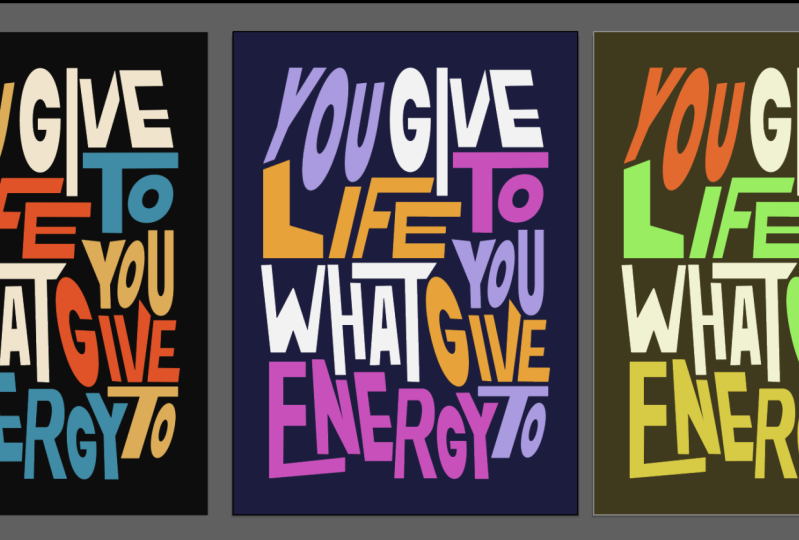
Design de cartaz de tipografia
Introdução ao curso - inspiração e referência
Lição 01 : Como desenhar o primeiro cartaz - distorção tipográfica básica e composição de grade
Lição 02 : Tipografia levou composição - distorção tipográfica individual
Lição 03 : Composição dinâmica de cartaz - distorção de forma e composição
Lição 04 : Elementos finais e pós-produção no Adobe Photoshop
Olá a todos e bem-vindo ao meu curso Skillshare!
Hoje vamos projetar estes 3 diferentes cartazes de tipografia contemporâneo,
A maioria do design será feita no Illustrator usando 3 técnicas e abordagens diferentes para o design e alguns toques finais e desenham alguns detalhes no photoshop
Tenho certeza de que você vai se divertir com este tutorial e você vai ter algumas novas técnicas em sua manga
1. Trailer do curso: Olá a todos. Meu nome é Marcus, animador de designer de animais. Hoje vamos projetar esses três diferentes cartazes de tipografia contemporânea. A maior parte do design será feita no Illustrator usando três técnicas diferentes e três abordagens diferentes para o projeto. E então faremos alguns toques finais e funil. Estes são detalhes no Photoshop. Tenho certeza que você vai se divertir muito fazendo este tutorial. E eu tenho certeza que você vai ter algumas novas técnicas para colocar em sua manga. Então não se esqueça de se inscrever e se juntar a mim na aula. 2. Introdução do curso - Inspiração e referência: Olá a todos e bem-vindos à primeira lição. Primeiro, eu só queria compartilhar com você de onde eu tirei essa inspiração. Estes são, na verdade, estes cartazes. Eu cuido disso. Vi-os no Pinterest e depois fui procurar. Quem foi o designer que começou este tipo de estilo. E porque eu estava pensando que era muito legal e eu realmente queria experimentar com este título também. Então eu gostei de alguns cartazes enchendo isso, fazendo este estilo. E eu só queria compartilhar com vocês o portfólio de designers. Então seu nome é Chris Andrew Small e ele é nosso designer australiano. E assim que vi o trabalho dele, fiquei fascinado pelo uso da tipografia. Eu tenho sido antipática para o último, eu acho, para o último ano ou assim. Tenho andado obcecado com o trabalho de tipografia. Eu tenho visto tanto conteúdo no Instagram sobre como topografia cinética, bem como mover topografia e novos tipos de ondas para usar tipografia normalmente como eu fiz a classe antes, como tipografia, eu senti um ligeiras elifs como no mundo do design vive em um muito, em um tipo muito rigoroso em direção a um mundo sério. E quando vejo alguém fazendo, estou me divertindo tanto com a tipografia e fazendo desenhos tão bonitos e quebrando todas as regras de sempre. Tipo, apenas como obter um tipo e apenas distorcido assim. E experimente cores e contrastes entre as formas. E então apenas criando isso como composições interessantes com ele. Eu estava fascinado com o seu trabalho e eu só decidi explorar um pouco para mim mesmo, algumas pausas caindo neste estilo talvez tentou obter algum conhecimento são liberados também porque o Ártico é como, não é como ele tudo bem para se inspirar e às vezes até copiar outros. Pessoas, designers trabalham porque você parece que tentou recriar algo. Você realmente tentou entrar na mente daquela pessoa e tentar ver o que ela vê. E nunca mais será o mesmo porque você sempre terá sua própria opinião sobre ele. Não é como se eu estivesse apenas criando o Saclay, este aqui. Agora, você só vai usar o mesmo tipo de estilo, mas isso nunca vai ser a mesma voz porque isso é exclusivo para você, como se sua abordagem fosse diferente. Por isso, está tudo bem se você apenas inspirar-se onde outras pessoas, Tenho certeza Chris, Andrew Coats inspirado por alguns em algum lugar também. Assim como uma mistura de respirações e realmente só queria compartilhar com vocês este é o portfólio primeiro porque eu acho que é realmente, eu não acho que você deve verificar. E eu acho que é incrível. 3. Aula 01: como criar o primeiro pôster — distorção de tipografia e composição de grade: Então eu vou mostrar primeiro que repórteres vamos projetar. Então o projeto final será feito para uma loja. Na verdade, isso é exatamente como as formas vetoriais. E o primeiro que vamos começar é este. Outra coisa que eu queria compartilhar com vocês é que eu criei uma biblioteca para este curso, que vai estar em seus arquivos Skillshare. Certifique-se de baixar a biblioteca. Você terá as cores e a arte real. E para isso, basta ir às bibliotecas aqui. Se você não tem a guia da biblioteca aqui, você pode simplesmente ir para Janela e tentar encontrar suas bibliotecas aqui. E depois vamos para a biblioteca Importar. Selecione o destino da biblioteca. Eu já salvei o meu aqui. Então você vai ter este arquivo na pasta. E assim que importamos, basta clicar em abrir e importar. E você vai ter todas as cores que eu uso nesses cartazes. E os cartazes reais e reais no caso de você querer abri-los e dar uma olhada. Se você apenas clicar e arrastar e soltar assim, você vai simplesmente soltá-lo. Se você quiser ir para dentro do vetor, você pode simplesmente selecionar Embed (Incorporar). E então nós vamos apenas incorporar a arte aqui e você pode apenas desagrupar e , em seguida, liberar a máscara de recorte. E tudo o que você tem agora é um arquivo vetorial. E você só precisa liberar máscaras de recorte até que você realmente tenha toda a capacidade do arquivo. Bem, vamos começar o nosso primeiro cartaz para que as escolas de direito se tornem novas. Vamos mostrar-lhe esta resolução realmente vai torná-la vertical 358 por 4961. Isto é mais ou menos como um cartaz A3. Então vamos dar um nome a este cartaz do Skillshare. Um. E vamos pressionar Ok. Desculpe se estou falando rápido demais. Tento não fazer essa aula esperar muito tempo. Eu não sei. Eu sinto que às vezes eu gosto de ser como sótão é mais dinâmico se ainda ensino é digitado até a velocidade e não leva muito para aqueles funcionários ou explicando ou muito lento. Eu gosto de mantê-lo, mantém-me incrível envolvido na classe. Então, para essas classes, eu realmente uso algumas citações inspiradoras de um Oriente Médio na verdade, e eu tenho que compartilhar isso em arquivos também. E DC era como alguns pedidos de inspiração como da frente, mesmo de Provérbios Chineses, dois filósofos para músicos, até intrapreneurs atuais. E é como eu faço, eu faço lei, eu acho que é como se houvesse muito poder nesses códigos. E às vezes eu os leio e eles fazem é como Orozco para mim. Às vezes eu os leio e eles me inspiram ou fazem sentido para mim naquele momento. Então eu gosto de ler um pelo menos por dia e eu gosto de usá-los tanto quanto eu posso para o meu trabalho pessoal, que foi o que eu fiz naqueles cartazes. Então o primeiro que você vai usar é de uma abundância de Napoleon Hill. E um objetivo é um sonho com um prazo porque você não quer esse arquivo. Ele estará na pasta Skillshare. Selecione qualquer um desses códigos como quiser. É que eu tentei não usar muito longos porque ele vai te dar mais. Você pode selecionar o tempo que quiser. Mas quanto mais palavras você tiver, mais tempo você vai precisar para colocar cada palavra, que pode ser mobília como você tem mais para experimentar por todos, apenas tente usar como uma muito curta por enquanto. E talvez depois de fazer este curso, mesmo se você fizer este tipo de estilo novamente, você deve explorar como esperar mais com certeza. Então eu vou usar este aqui. Vou copiar e colar isto. E eu vou usar a ferramenta de texto no Illustrator para apenas colar a escala de canto. Um sonho é um objetivo. Um objetivo é um sonho com um prazo. Bela turnê. Eu realmente gostaria de usar realmente um muito bom, como um VLC cubículos de ética é uma fonte que funciona como você faria qualquer coisa. E quando eu não tenho certeza que tipo de fonte eu vou usar para qualquer projeto. E se e se ele for como um projeto cliente, 90% das vezes eles já terão uma fonte. Mas se eles não têm, eu vou para o cuidado veterinário ou algodão ou para turnê. E eu só vou para o personagem aqui. E eu vou fazer tudo isso. Então vamos apenas, a primeira coisa que realmente você precisa fazer é expandir seus testes, seu texto. Certifique-se de que está satisfeito com o código. Porque assim que expandirmos isso, não seremos mais capazes de editar o texto. Se você quiser pode apenas fazer uma cópia disso, talvez ir para editar. Copiar, Editar, Colar. Deixe aqui apenas por segurança, caso queira alterar isso por algum motivo ou alterar a fonte. Então vamos começar. Vamos para Object e ir para Expandir. Imprensa. Está bem, Perfeito. Então a coisa sobre o estilo que eu mais gosto é de laticínios, sem regras sobre como você trata a fonte dele. Você pode esticá-lo para cima ou para baixo. Você não precisa realmente gostar, você sabe, quando você está projetando, você precisa realmente estar procurando o kerning e tentar entender distância e enquanto as proporções e como, é tão, é tão chato às vezes . E o estilo é tudo, mas não erro chato. Então, a maneira que eu gosto de fazer isso é apenas, vamos começar separando as palavras. Um objetivo é um sonho. Prazo. Ótima. Então você pode realmente, se quiser, você pode começar a criar algumas formas primeiro. E como vamos usar a ferramenta Retângulo, por exemplo. E apenas tentando criar algumas como começamos, formas aleatórias. Você não precisa seguir nenhuma nota. Podíamos fazer uma grelha e seguir a grelha, mas isto é para ser tão livre quanto nós, quanto pudermos. Acho que se todos puderem lê-lo como designer, já temos regras demais. Então vamos saber se temos regras aqui e não há grades em tudo. Então, vamos apenas para aqui. Você pode ir para a luz que você elaborou, manter apenas importante e usar minhas cores, se você quiser. Caso contrário, você pode simplesmente ir para as amostras de cores aqui. Encontre uma amostra realmente agradável para o seu cartaz. Adoro o Papa devastado pela guerra. E você pode simplesmente explorar todas as cores incríveis que já estão nas bibliotecas do Illustrator. Ou você pode simplesmente ir para equipes de cores e tentar encontrar uma cor realmente agradável para ele e apenas usado para ele. Não se sinta forçado a usar minhas cores. Por favor, tenha certeza que está. Você realmente explorar mais cores e eu vou tentar não gastar muito tempo em cores nesta classe porque eu queria fazer uma carga. E, mas eu tenho certeza que você pode apenas usar este Explorer na cor, Adobe Color Themes será, você está pronto para ir. É uma seleção incrível aqui. Só vou fechar isto por enquanto. Então vamos começar. Então você pode começar como eu disse, como apenas bloquear algumas formas ao redor e então usar seus textos. Eles estão tipo, eu estou pensando em talvez como esta forma preta aqui. Vou ao Comando C, comando F para colar no lugar. Vou fazê-lo usar esta cor rosa aqui. E agora vou me fazer perder minha primeira palavra. Vou fazer isto largo. Vamos apenas selecionar este sólido preto porque ele está na frente de uma carta e eu vou arrumar e vendê-lo para trás. E eles vão usar esta ferramenta de distorção aqui, a ferramenta de transformação livre. Se você clicar em E, apenas vai empurrá-lo para cima. Aqui. Isto é, é bom fazer isto. Por alguma razão. Se meus diretores de arte, alguns fazendo isso com o nosso, no nosso trabalho, ela só vai mostrar, apenas me matar. Não posso fazer isso com fontes. Mas a coisa é como, eu acho que nós, nós devemos ter tempo para jogar. Eu acho que é quando você parar de jogar e se divertir com o design é quando você começa, quando você apenas diz quando ele começa a ser apenas um trabalho e não como um hobby ou como realmente algo que você gosta de fazer? Eu acho que para eu não jogar por anos. Como designer, eu só tinha trabalho de cliente e eu apenas fiz isso, eu não sei, por um longo tempo sem fazer nenhum experimento pessoal ou projeto pessoal. E eu podia sentir como se eu não fosse Thai Wah começar a odiar. Mas eu estava começando a não gostar como eu costumava desfrutar do meu profissional como quando eu comecei. Então este é um, eu vou apenas arrastar o objetivo agora, clique com o botão direito do mouse. Traga-o para a frente. - Sim. Então eu acho que é importante também para você, assim como, você sabe, é importante para você ir lá fora e dar um passeio na natureza. Eu acho que é importante também, ir lá fora no Illustrator e apenas ter um, ter um ir. Apenas se divirta, sabe? Não, apenas criando algo. Ou mesmo assim como eu fiz, apenas ir como no Pinterest, encontrar algo realmente legal e tentar recriá-lo de alguma forma e tentar torná-lo o seu site, para torná-lo o seu estilo. Então agora, como se eu estivesse distorcido é um pouco, mas em um objetivo, eu realmente quero começar a distorcer o isqueiro como igual. Eu quero fazer alguns deles mais. Talvez como eu faça as distorções individuais. Em vez de ser um grupo mais velho. Como este. Talvez a fazer algo assim. É só que talvez você vá levantar essa perna. São todos distorcidos ainda mais do que um, algo como. Então, o primeiro pôster, eu só quero pedir para explorar como apenas distorções de escala, não como tantas rotações. E é como um aquecimento para o que vem a seguir. Então o objetivo é que eu vou, eu realmente não posso fazer o simples, desculpe eu fiz antes. Isso. Como exemplo, eu te mostrei aqui. Porque é como, ele, realmente depende do momento em que você está fazendo isso. É como se toda vez que você vai fazer este processador, ele vai recriar. Ele terá um olhar diferente projetado para que a técnica será definitivamente a mesma. Assim como explorar formas e formas. Um gol. Talvez você possa escalar esses dias para jogar com contraste líquido e posição também. Você sabe, como um gol, você não precisa. Mais uma vez, temos esta caixa aqui para, para referência. Embora possamos, podemos brincar com a caixa o quanto quisermos também. Você não precisa ser muito precioso sobre, sobre a caixa. Como, novamente, nós não queremos grades é como diretrizes que não podemos seguir era. Então um objetivo é, vamos apenas agora fazer é um objetivo é meio como este, mas são realmente precisa fazer é criar alguma separação entre as letras. Caso contrário, parece que ele é a mesma palavra como goleiros, em vez de dois momentos diferentes do vocabulário. Isso faz sentido. Oh desculpe, eu só uso um atalho, mas você pode apenas selecionar a forma aqui e organizar e enviar para, você tem o atalho aqui. Vou mandar para trás e providenciar. Enviar para Voltar. O objetivo é apenas talvez escolher, talvez mudanças muito largas. Talvez voltes a brincar com a esfera de distorção. Por favor, certifique-se de encontrar como obter como um código realmente agradável a partir dessa lista e, e jogar ao redor. A realmente quero ver como porque eu tenho certeza que algumas pessoas vão escolher os mesmos códigos para. Você pode até adicionar como eu fiz agora. Você pode simplesmente adicionar novos elementos à sua fonte. Não há nenhuma promessa. Erro. Ir embora estava dizendo que é exatamente como eu tenho certeza que algumas pessoas vão escolher o mesmo, o mesmo frio, a ferramenta Simcoe falar com pessoas diferentes. E eu realmente quero ver como, como, como você é isso, como você desenha, como será diferente ou você sabe, como algo como duas pessoas podem ter o mesmo código e devido a dois diferentes projeta cuidadosamente. E até mesmo a faculdade, eu acho que as cores nesses exercícios são tão essenciais porque é como se você estivesse brincando com contraste e formas e você está definitivamente confuso com todas as regras da tipografia. Mas a cor também ajuda, como ajuda muito a mensagem aqui. Vamos continuar mudando isso até que pareça certo. A coisa se um telefone às vezes projetar é um pouco como É um pouco de um sentimento. Às vezes é como você, você sente que não está lá ainda, mesmo quando parece bom. Vamos continuar empurrando. E então é, então você prazo para o que é leste o fio é projetado e o que é arte torna-se realmente difícil de definir para mim, pelo menos. Por isso, às vezes penso que o design é uma conjunção de função e arte. E não sei se isso é uma corrente. Onde é que é isso? A Nike também é branca. Talvez eu distorça este slide. E novamente, você, isso, isso é sobre apenas experimentar e descarregar tudo. Isso é sobre como se você é um diretor, diz que isso é sobre fazer, estão realmente com fome ou Ei, eu estou realmente com raiva. Como o quê? O que você está fazendo é descarregar o objetivo está bem, legal. Apenas empurre isso. Talvez, na verdade, nós vamos então nós vamos fazer isso um objetivo é. E então talvez você possa apenas continuar experimentando até que você sinta que está certo e você pode sempre voltar aqui. E a justiça. Agora vamos usar escala aqui. Então esta é a escala de uso. Sim, Então, para vir enchendo mais melhor , este aqui, às vezes, é complicado jogar com o contraste das formas também. Sim, acho que acha que estou feliz com isso. E agora vamos sonhar. Então, até você usar o mesmo estilo que eu uso em um primeiro pôster, que eu uso o A para preencher todo este espaço. Cria uma forma muito agradável. E como esse tipo de efeito de flecha, que é muito legal. Então eu vou apenas fazer uma nova caixa aqui usando a ferramenta de retângulo aqui. E eu vou encontrar uma cor para isso. Talvez possa ser azul. Rosa agora, filtro azul, certo? Por que eles estão realmente bonitos? Então, quando terminarmos todos os cartazes, vamos levá-los ao Photoshop. E lá vamos fazer, adicionar um pouco mais de detalhes, como alguns rabiscos sobre ele então. Mais como mais detalhes de ruído e tornando isso um pouco mais interessante. Então, tudo bem se você sair como um espaço vazio como este. Porque então podemos, podemos ter mais, alguns detalhes sobre para um SharePoint que, como você vai ver em breve. Um objetivo é um sonho. O sonho é um sonho. Então palavras realmente bonitas que chamam de um sonho, mas eu vou apenas distorcido como este chamado os olhos Filson. E mesmo como, sabe, quando você faz isso, você sente como se estivesse destruindo. Mas é apenas tornando a deformação mais, mais interessante é como apenas tornar isso mais útil para o, para os olhos. Sabe, é mais interessante porque se você colocar isso na moldura branca deles usando o lago, está tudo bem, você recebe a mensagem e é importante, mas quando você faz assim, Você recebe a mensagem e recebe outra coisa. Há algo diferente. Você tem uma sensação de letra diferente. Você vai ler. E você também experimenta uma sensação ou social o suficiente como talvez você não goste, mas ainda assim uma sensação, parece que um sentimento está lendo e algo diferente não é apenas ler está experimentando uma mensagem. Acho que no Dream é uma árvore. Eu vou apenas fazer isso. E talvez moeda para. Só tenha certeza de que não distorce muito. Então você vai realmente perder a forma da letra. Você ainda precisa entender que dizer que eu sou um a e um são de outra forma, então você a mensagem será, não será tão clara quanto precisa ser, para ser capaz de lê-lo não rapidamente, mas para lê-lo. Como se você não quisesse ser como algo irracional no único A-frame. Caso contrário, você pode apenas obter os interesses para o visual, mas então você pode perder o interesse pela informação. E a informação também é, é. Também é importante como, tão importante quanto um visual. Só vou selecionar isso. Um objetivo é um sonho com um prazo. vez, temos uma letra um, que é como realizado, citado porque eu gosto do porque alguns seta Osaka o tempo todo. Só resolvemos uma fonte Attica. E eu gosto desse sentimento de como apontar para algum lugar. E a dinâmica de um tipo de esconderijo mostra que eu realmente, bem. Só vou usar preto. Perfeito. É um sonho com um prazo. Não sei se vou tentar isto. Talvez ele crie como um pouco de boca, mais dificuldade para entender o que está escrito aqui. Usando um teste como este. Mas acho que cria um visual agradável e agradável também. Eu acho que ele cria como um bom nome dinâmico e matriz porque você tem um objetivo é um sonho. E depois vamos para baixo com esse prazo. Nós bactérias vamos sair assim, apenas certifique-se de criar um fundo sólido. Faça-o branco. Empurre para trás. O objetivo é um sonho com um prazo. Talvez possamos tocar um pouco para a composição aqui. A estrela para também ter certeza de, como distorções personalizadas para cada letra é que ele cria como uma outra camada de interesses de interpretação assunto sobre ele. Como traços indo para, talvez você está indo para empurrar o a e fazer o n. Então eles não têm como o, porque quando você interrompe-los completamente, ele ainda sente que eles são dados como esse. É que esse é o estilo deles. E quando você faz distorções diferentes para cada um deles? Você pode sentir que, oh, este é realmente um novo dia diferente. Isso é, na verdade, talvez um por um. Só vou adiar o prazo. É só ver se funciona. Agora, como você pode ver, às vezes funciona muito bem horizontalmente. Ele realmente precisa funcionar bem na vertical. Então eu só vou, talvez eu apenas empurre isso assim. Então não faço outra maneira. Sim. Então este é o primeiro. E depois de desenhar o cartaz seguindo esse tipo de solução, eu meio que gosto de relaxar no pulsar de alcatrão e então eu vou agrupá-lo. E agora L, quando você se move, você apenas selecioná-lo e você se move. Tão completamente. A próxima coisa que vamos ser percebidos a fazer é, na verdade, reduzi-lo um pouco para baixo. Vamos matá-lo como 90 por cento. Algo como isto. Eu faço isso porque eu realmente gosto de assinar esses cartazes. Como se esse código fosse. Vamos colocar como frio pelo tamanho é chamado Napoleon Hill. Então precisamos dar algum crédito para o, para o código mais quente. Citação de Napoleon Hill. E habilidade este pouco para baixo. Talvez 35. 35 aqui. Vamos fazer um desenho de Marcos. E faça o mesmo. Certifique-se de dar crédito ao, para o criador do código. E, novamente, também dê crédito para o design do portfólio. E não se esqueça de, se você, se você tem Instagram ou alguns alguma rede social, se você postar o eficiente é, por favor, certifique-se de me marcar. Eu adoraria ver e compartilhar seu trabalho também. Meus, meus, meus seguidores. E eu realmente gosto de permitir realmente como quando, quando realmente ver como o que vocês fazem quando vocês postam projetos na seção de projetos da classe? Diz que toda vez que temos uma notificação e eu vejo, é tão bom para mim porque é como, oh, alguém, eles são, alguém realmente teve tempo para fazer essa aula. E eu espero que eles gostem de cada um de mim também vendo o trabalho de finalistas, você sabe, porque é como se isso tornasse minha classe mais real para mim de alguma forma. Então vamos fazer um aqui. Vamos apenas alinhar isto. Certifique-se de que não precisa. Bem, por que não? Só fazer uma parada completa por aí? Sim. Então, sim, este é o nosso primeiro pôster feito. Teremos este pulsar no Photoshop mais tarde, quando tivermos todos os pulsares de árvore. E então vamos fazer alguma pós-produção em todos eles de uma só vez. Então, não precisamos pular do Photoshop e voltar para o Illustrator. Vamos fazer nosso próprio trabalho no Illustrator agora. E depois saltamos para o Photoshop. 4. Aula 02: tipografia em composição — distorção de tipografia tipográfica individual: Olá e bem-vindos ao segundo cartaz. Então vamos usar a mesma resolução de antes, 3008 por 4961 orientação vertical. E isso é ótimo. Assim, o primeiro redesenho do cartaz, este aqui, usamos formas para nos ajudar a, para a composição dos textos dentro dessas formas. Então este é um bom exercício para começar, como porque é, é mais fácil encontrar o equilíbrio certo. Nós moldamos primeiro e depois exploramos os textos dentro dessas formas na literatura do segundo cartaz. Então abertamente exemplo aqui, nós realmente queremos usar os textos como, como o centro principal da composição. Como não temos nenhuma forma aqui, vamos brincar mais com o peso do texto. Então nós apertamos, nós íamos distorcer um pouco de textos, um pouco mais. Vamos girá-lo. E toda a compensação será liderada pelo texto e pela topografia. Então vamos pular. Então adotivo dois são usados. Outro casaco e novamente está nas listas. Eu só compartilho com você, desculpe, e palpites. Meu cérebro começa a ficar congelado porque eu gravo essas aulas na noite em que minha namorada está assistindo TV e eu terminei meu trabalho. E eu digo: “Sabes que mais, vou fazer uma aula de Skillshare”. E, às vezes, sou um pouco cansativo e o meu cérebro pára, tipo, o que mais dizer a seguir? Tentei fazer roteiros para essas aulas, mas piorou as coisas. Então eu não sou agora eu sei o que eu vou fazer. Faço a aula primeiro comigo mesmo e depois tentei recriar o exercício. E a ação se sente melhor porque se sente evento mais natural para mim. Tão arrependido. Depois disso separados. A cota que você vai usar é um investimento em conhecimento, paga o melhor interesse de Benjamin Franklin. Na verdade, Benjamin Franklin, nota lateral, é um ser humano muito interessante. Tenho aprendido sobre coisas de saúde como dormir melhor e jejum. E Benjamin Franklin, ele apenas, ele era apenas um incrível como a maneira como cuidar de seu cérebro e corpo era algo insano. E é realmente um cara muito inteligente, com certeza. Portanto, um investimento em conhecimento paga os melhores interesses. Bem, Skillshare está aqui para provar isso. Vamos fazer essa aula. Desculpe, vou parar de falar sobre funcionários que não são relacionados à aula. Então vamos copiar e colar novamente aqui. Um investimento em conhecimento com as notas de melhor interesse. Sei que, na verdade, tenho feito design há menos de 10 anos. E as melhores coisas que obtenho da minha carreira é como o Times realmente aprendeu com outras pessoas e com os cursos que fiz quando fui, na verdade, começaram a minha carreira. Skillshare não era uma coisa ainda. E eu costumava comprar DVDs online e o era tão caro e nos escapa como nós, eu e meus amigos da universidade vamos ficar juntos. E eu acho que como se fosse uma série que custaria como algo como 200 Euros de GetNumWords, escola de efeitos visuais e para After Effects. E nós só nos juntamos e compramos juntos e depois compartilhamos os DVDs um com o outro? Bem como diferentes épocas e 200 anos, 10 anos atrás era muito dinheiro para nós. Ainda muito dinheiro, mas foi divertido e eu realmente ensino no Skillshare porque é tão acessível para todos. E, você sabe, é como se pudesse ser algo realmente profundo sobre alguma técnica, ou poderia ser apenas algo que fica muito divertido de fazer. E podemos fazer isso juntos. E eu nunca tive como este tipo de e mesmo como os tutoriais sobre Skillshare são mais experimentais e 1980, é algo realmente interessante para mim porque como você não segue passo a passo e você todos nós temos o mesmo resultado. No final, você sabe, antes que eu pense que os tutoriais são usados para adivinhar, obter como 10 anos atrás, os rendimentos seguem passo a passo. Você vai gostar de um livro de receitas. E no final, você será r teria o mesmo reforço ou o mesmo design. Exatamente o mesmo. E os cursos que eu tenho feito, feito no Skillshare principalmente é tão criativo, é mais criativo orientado com preto. Você pode aprender uma técnica e desfrutar de explorar. E eu nunca vi duas pessoas terem sido vários resultados. Então vamos começar com isso. Sinto muito pelo meu murmúrio agora. Eu só queria compartilhar isso com você. Ok, então qualquer investimento em conhecimento paga os melhores interesses. 70. Mais uma vez, vou financiar obter LV Attica. Outra dica é se você já assistiu o velho documentário da Vertica, veja isso é, É realmente incrível. E vamos ao Object e ao plano X. Ótima. Cmt nos permite selecionar prêmios e desagrupar isso e colocar portas distância uns dos outros. Então, você sabe, eu realmente esqueci de fazer isso tudo em maiúsculas. Eu fiz um monte de comentários. Sr. E todos os bonés. Talvez não. Bolt. Vou criar esboços. Você pode clicar com o botão direito do mouse e criar contornos, ou ele pode ir para Objeto e ir para Expandir. Mesma coisa. E você também pode ver que o atalho é Command Shift O e os contornos que x é a maior coisa que enquanto software há milhões de maneiras de fazer uma coisa. E vamos para um investimento na base de conhecimento. Os melhores interesses. Na verdade, isso já é, pode já ser alguma coisa. Acho que gosto da forma como esta é a dinâmica dos decks acontecendo aqui. Um investimento em conhecimento, talvez o conhecimento deva ser um pouco baixo. É como um passo. Se você gosta top poucos oferecem alguém passos. Está bem, mas não é isso que vamos fazer hoje. Então vamos selecionar n e apenas usando a ferramenta de transformação livre, Vamos começar a distorcer isso é fede primeiro, e vamos apenas empurrar este também. Então, ok, vamos apenas, então agora nós vamos realmente tão doce, não temos formas. Nós vamos realmente usar o tipo para criar algumas composições dinâmicas como esta. Só vai ganhar vai apenas torcer assim e então talvez brincar com o n. Talvez seja apenas empurrar o N um pouco. Como na verdade, vamos, vamos ver, vamos ver o que é o que os textos nos dirão e investimento. Ok, eu posso ver isso acontecendo. Oi, Miguel. empurre o “N Talvezempurre o “N”. Eu só vou fazer isso. Ok, não vamos esquecer de usar as novas cores se você quiser. Se você não quiser, por favor, não se sinta forçado a usá-los. E só tentando distorcer essa coisa. Novamente, apenas tendo o máximo de diversão que puder. Como ninguém está olhando, ninguém está aqui para julgá-lo. Eu acho que não ser louco é a coisa louca é apenas empurrar isso para baixo e tentar inovar. Tente encontrar a perna direita. Composição como técnicos de rádio tentou empurrar, diz, tentou ser negrito que você não precisa gostar, e se não está funcionando no escopo de volta nota inicial. Então, de uma maneira diferente. Talvez seja uma separação melhor entre o tipo e as letras. E eu só vou empurrar isso. Agora você não quer perder um vicioso indo para um investimento e apenas tentando fazer isso. Você também pode selecionar os pontos usando a ferramenta de seleção. Se você clicar em um também, você não pode simplesmente puxar esses pontos e novo, você apenas distorcer a tipografia ainda um pouco mais. E veja o quão longe você pode realmente chegar. Eu tenho outra classe no Skillshare e que é criar um formulário diferente usando fonte antes. É topografia personalizada do experimento, por favor, confira. Sim, tenho certeza que se você tivesse gostado desta aula, você não iria gostar dessa também. Vamos empurrar isso para baixo. Tente jogar com isso como usar um novamente aqui. Talvez só empurrar isso. Há um líder. Como se não estivessem lá. É que às vezes eu não quero lutar com ilustrador sueco e tudo bem. Experiência talvez, na verdade, quando há um aqui, eu vou distorcido t. novamente. Certifique-se de não ter medo de fazer edição porque é, É apenas experimentos que você realmente, quando você joga é quando você realmente aprender mais, é quando você realmente, você pode levar isso no futuro para algo Totalmente diferente. Você sabe, como quando você aprende que, como uma nova técnica que você aprendeu nesta aula, que então você pode usar realmente para o seu trabalho real ou a vida são totalmente diferentes exercícios, mas é quando você explora como aqui. É, você nunca sabe onde, onde isso vai te levar, ou quando você realmente vai usar isso, ou quando você quer realmente ter a chance. Imagine se você tiver a chance de, na verdade, alguém vê seu pôster e diz: “ Oh, eu quero isso. Será porque você o explorou. Não seremos porque está em você, porque é exclusivo para você. E essa é a beleza de não fazer um design tradicional. Pratos de cartaz porque se torna único, é torna-se diferente e Garros mais atenção. Então, quanto mais você jogar, melhor. Vamos continuar empurrando isso. Eu gosto da forma como isto, isto, esta rede que eu gosto de trabalhar em negrito não são realmente, não tenho certeza sobre alguns deles na verdade, talvez o n é parece realmente distorcer este pouco mais. Sinto que estamos perdendo alguma legibilidade e investimento. E mais uma vez, está tudo bem. Você pode apenas, você pode apenas realmente usar também algumas ferramentas para distorção de padrão. Isso é apenas pode selecionar este grupo que. Então ferramenta de distorção novamente. Oh certeza de que você pode apenas brincar com como tentar distorcê-lo usando nossa ferramenta de cisalhamento aqui, ou mesmo como nossa ferramenta de forma. Agora, na verdade, vamos brincar com essas ferramentas de movimentos aqui, a ferramenta de cisalhamento que eu acho é que ele ajuda muito sempre que queremos experimentar com uma perspectiva diferente sobre isso, em um texto. Como se você não se sentisse muito feliz com a posição. Você pode simplesmente brincar com a ferramenta de cisalhamento e ver onde ela o leva. Principalmente. Você vai apenas fazer isso. Então, o “A” realmente se senta lá, algo assim. Só estou tentando jogar assim. Perfeito e investimento em, costurado é uma coisa grande e nós só precisamos fazê-lo. Porque enquanto você lê isso, você vai querer ter certeza de que você mantém o, a seqüência do código indo. Então vamos apenas para n e apenas jogar um pouco também é, mas não muito louco. Por isso, não perdemos o significado deste casaco. Como não significar sua legibilidade deste código. Desculpe, um investimento. Conhecimento. Então o barulho tem um muito grande. Talvez possamos brincar um pouco mais com conhecimento. Só vou empurrar isso para cima. Acabei de começar. Empurre aqui. Chumbo. Eu posso destruição individual como para tornar o texto um pouco mais interessante. Não perder totalmente a forma da letra. Talvez usando um empurrão. Sim, algo assim. Podemos brincar com a posição das letras também. Portanto, não é uma distorção, mas também algumas composições dinâmicas com a posição das letras é um investimento no conhecimento. Veja como, mesmo como agora, parece tão dinâmico e você ainda pode lê-lo. Você provavelmente vai levar um pouco de tempo. Quando você leva mais de dois a cinco segundos para lê-lo, talvez ele deva apenas como eu acho que é como ver o que está impedindo. Não está a ajudar-te. Neste caso. Eu acho que o n, É talvez um pouco de lata e nós realmente perder a capacidade de lê-lo como o fim realmente rápido. E provavelmente vou tentar fazê-la voltar a ser um pouco legível como nós antes. Só vou selecionar assim, talvez usando nossa ferramenta de cisalhamento novamente. Ou talvez apenas na verdade vai apenas apagar este n. Eu vou usar este aqui. E eu vou usar este aqui porque não há problema em fazer isso. Um investimento em conhecimento. Eu acho que conhecimento e experimentação, há um monte de periodontal de conhecimento em experimentação e experimentos, mas foi, não, foi medo de experimentar definitivamente não é. Um investimento em conhecimento, paga o melhor interesse. Novamente, talvez eu esteja indo para jogar com p. E eu vou, usando a ferramenta de seleção aqui, poderia empurrar esses pontos um pouco. Uh, como esta peça clínica, uma carta tão bonita para brincar. Porque é a forma da letra P é algo como Laker é como uma Tammy algum como se isso faz sentido, é como um guarda-chuva, tipo 5. Você vê, você pode colocar algumas letras aqui embaixo e fica muito bom. Novamente, alguma distorção individual como esta. Talvez, talvez por que nossa vontade de realmente ampla pode apenas ok. Dividir. Vamos brincar com a largura assim, como a maneira. Embora eu acho que devemos brincar com alguma parte dessas cartas com certeza. Vamos usar o cisalhamento para tentar não perdê-lo. Basta usar a ferramenta de distorção livre. E tente encontrar uma boa composição para isso. Ok? Paga o melhor. Veja, isso já é uma citação muito longa, que está me dando um pouco mais de trabalho para redefinir tudo. É por isso que eu disse, se você tentar, se é a primeira vez que você está fazendo este exercício, certifique-se de usar como um código mais curto para a primeira experimentação. Então você não passa menos tempo fazendo a composição e mais tempo brincando com ela. Você sabe, porque quantas cartas você tiver, mais difícil será. Portanto, apenas esteja ciente dos dados, na verdade, apenas esteja ciente de que você provavelmente vai se sentir provavelmente apenas fazendo isso pela primeira vez. Esteja ciente também. Para tentar encontrar como um código muito bom, fácil para o, vamos apenas brincar. Veja você pode, você pode até mesmo estender letras para que eles realmente se conectem uns com os outros de uma certa maneira. O conhecimento, base de conhecimento são os melhores interesses? Então as abelhas são realmente interessante letra bem para trabalhar. Então isso é apenas um interesse é uma palavra muito longa, mas vai ser um ritmo certo. A melhor habilidade desta prática, brincar, contrasta. Como você pode ver aqui. Nós apenas torcemos uma matriz muito magricela aqui e muito ousado B e T e este bonito como talvez escala isso. Jogar com, com movimento, bem como uma pequena dinâmica como você pode fazer a sua conclusão, o melhor, o mais interessante. Ele vai olhar em algum lugar os olhos de outra pessoa, interesses. São palavras muito longas. Vamos ver o que podemos fazer. É que você pode mantê-lo simples também. Se você, se você sente como, se você sente que sua aversão é um código muito longo, e se você sentir como adicionar mais detalhes e distorção vai realmente torná-lo mais difícil, você pode apenas, você sabe, eu vou apenas parar aqui e apenas fazer um muito, muito simples. Não tão, não tão louco. A composição, Nós, as destruições, baseamos os melhores interesses. Na verdade, vai gostar disto. Basta empurrá-lo para baixo. Novamente, distorça isso um pouco mais usando o L aqui. Legal para as regras do terrorismo novamente, como eu disse antes, você continua experimentando. Como eu, eu faço, eu vou fazer realmente assim. Eu sinto que é uma jornada projetando esse tipo de bens porque é um cartaz, desculpe. É porque é como se precisasses, não sabes para onde vais. Não há nenhuma maneira de definição. Não há nenhuma diretriz como Oh, o resultado final será assim. Então o resultado será, se não houver uma maneira que você possa saber que depende tanto do momento é um tipo de design tão presente porque não há livro de marca para isso. É campo é, é realmente perto de criar sua própria peça de arte pessoal ou domingo. Não estou dizendo que isso é uma farsa ou algo assim. Só estou dizendo que é como se sente quando você está criando algo como design e arte. E bem, eu gosto, eu até gostei de uma primeira versão Beck e branco porque é quando você acabou de trabalhar com tipografia, é melhor trabalhar com a composição primeiro. E para isso só usamos preto e branco porque ele trabalha totalmente em preto e branco. Quando você adicionar cor será chegado, você sabe, você não precisa se preocupar. Então vamos apenas se você está feliz com sua versão em preto e branco, vá para a cor. Agora, novamente, podemos usar minha biblioteca aqui, ou você pode usar a sua e as que você escolheu. Então, na verdade, vou fazer fundo. Aqui, vou tentar usar as mesmas cores que usei antes. Então vamos tentar isso ao contrário. Selecionado, Organizar Enviar para trás. E vamos deixar este texto branco por enquanto. Mesmo como um invertido parece muito, muito bom. Então vamos apenas colocar um pouco de cor neste design. Agora. Vou selecionar uma lactose e selecionar o fundo. Vou adicionar esta cor rosa. Talvez pudesse usar as mesmas cores, mas não na mesma sequência. É realmente, é realmente como ter esses corais são prontos porque é, para mim é mais rápido, fazer este tutorial e realmente estar falando com você enquanto eu estou fazendo isso. Porque se eu fosse você, porque quando eu vou procurar cores também, eu queria dizer que eu posso ser apenas gasto como duas horas, apenas tentar encontrar um bom conjunto de cores ou on-line ou apenas obter uma cor. E então eu tentei encontrar outra cor que se encaixasse nessa cor. E então eu sou como as cores das árvores e eu não gosto mais delas. E é por isso que eu já fiz este conjunto de cores aqui. Então eu não te levo nessa jornada insana de eu tentar fazer uma paleta de cores para mim. Certo, então vamos manter o conhecimento. Eu acho que vou viver conhecimento branco. Eu vou pagar pacer vai torná-lo rosa. Cole o baixo. Vou te contar um segredo. Eu só, eu apenas amei fazer este tipo de design e eu amei tanto este estilo porque eu atualmente trabalho para uma empresa. Não é como se o meu trabalho fosse chato ou algo assim. É só que precisamos seguir as diretrizes da marca da empresa. Você pode ir assim sem motivo. Mas às vezes é um pouco rigoroso. E quando você tem que seguir como um livro de marca, você precisa manter a consistência. É como se você pudesse fazer algo totalmente diferente. Ele precisa fazer parte , precisa ser parte da marca da empresa. Este exercício me fez sentir tão aliviado, mas livre de alguma forma. Como se eu pudesse fazer o que eu quiser e eu posso distorcer a topografia assim porque é como o temporizador que você gasta digitação. Os EUA dele. É muita coisa. E é como liberar seu alcance. Raiva na tipografia. Sim, meio, meio assim. Uh, como a maneira como você pode ler de duas maneiras diferentes. Você pode jogá-lo como investimento, melhor, conhecimento, interesses, e, em seguida, n base. Mas a coisa é como você, quando você tem como cores e preto é branco, você sempre, seu cérebro vai sempre primeiro para os brancos quando eles, e então vai para a cor mais contraste. Isto é como a teoria das cores. E como eles chamam de valores brancos e negros. E você sempre vai ler os valores primeiro e então nós, você, você, você vai ler a saturação mais tarde. Então é como primeiro ler valores, que é preto e branco, e então você vai, você vai ler cores. E isso cria um layout descontraído, interessante porque é como se você pudesse ler isso, como conhecimento e turistas, pragas de investimento e paga no, é, é realmente um tipo, é muito agradável maneira de chamar a atenção. Para o principal. A principal mensagem que você quer é que você quer passar conhecimento e interesses. E às vezes você tem como em seu feed Instagram ou em seu trabalho, você só tem como uma fração de segundo para chamar a atenção de alguém. E usando a teoria das cores, é muito importante fazer isso. Então eles realmente pararam ou mesmo se ele não parou, a mensagem principal que a mensagem mais importante rouba em sua mente. Pelo menos. Desculpe, estou falando da teoria das cores agora. E sim, este é o possível número dois. E o próximo cartaz será arbitrário e o último. E depois disso, vamos terminar onde vamos fazer alguma pós-produção em nossos cartazes e exportar nossos arquivos finais. E então diga adeus. Mas ainda mais um cartaz para levar, então não vá embora. Vejo-te na próxima aula. 5. Aula 03: composição de pôster dinâmicos - distorção e composição com forma: Então árvore número cartaz e ok, vamos de novo, basta ir para minhas listas de citações. E este é de Aristóteles. Qualidade não é um ato. É um abade. Então vamos apenas para o nosso selecionar o nosso texto aqui. E, novamente, a qualidade não é um ato, é uma média. E tente como Doula o melhor que puder. E nós cronometramos o melhor que puder, vai ser melhor. E agora vou expandir-me como fizemos antes. Então o quanto você gosta, a maneira que você precisa fazer é como, nós precisamos ver quantas palavras nós temos. Temos um aqui. Só estou fazendo isso, só pelo exemplo. Agora qualidades, uma palavra é outra, não para outra. Então você tem que recompensas. Isso seria para o número de formas que precisamos projetar neste quadro aqui. Para. Você não precisa fazer isso. Só estou fazendo o exemplo. Mas, você sabe, você pode fazer isso se você tiver 67 anos. Eu quero fazer isso como uma palavra para que seja número quadrado. Então, agora o que vamos fazer, ele só está usando nossa ferramenta de caneta aqui. Você vai projetar o mais aleatório que puder. Algumas formas. Vamos usar, vou usar minhas cores aqui das bibliotecas que compartilho com vocês. E eu vou fazer este. E este será pela qualidade. Na verdade, vamos arrastar a qualidade até aqui e organizar, trazer para a frente. Certifique-se de crescer período. Cartas já agrupadas. Agora, selecione-os. Botão direito. Não me mostra isso, basta ir ao objeto e agrupá-los. Legal. E novamente aqui, tentou usar os mesmos lados do outro quadrado. Você pode fazer algo diferente se você quiser, mas vamos apenas tornar mais fácil para o bem do exemplo, ele não vai realmente usar essas duas palavras. Organize, traga para a frente, Object, Group. Agora, vamos fazer assim. Vai ficar azul. E isso será para um ato. Eu não acho que eu usaria um coma porque eu sou apenas parecendo você como uma empresa. Você não pode excluí-lo mais tarde e organizar, trazer para a frente. Talvez você faça isso mais interessante. Esta mais uma forma é assim. Faça-o amarelo. Talvez. Vamos manter assim. E então Abbott estará dentro dessa forma estranha. Lá para ser preto. Vamos passar por isso. Você pode simplesmente selecionar as letras e pressionar Command J ou Control Z. Ou você pode simplesmente ir para a edição aqui e este objeto aqui e aquele grupo, os elementos juntos. É um abade. Outra coisa que tenho tentado aprender. Meu escrutínio melhores hábitos da minha vida, mas é muito difícil de habitar. A criação é uma escala que ainda trabalha nela. E tudo bem. Então, sim, precisamos compartilhar, dividir, os prêmios em torno dessas formas que acabamos de criar. E a próxima coisa que precisamos fazer é simplesmente duplicar essa forma. Você vai para objeto, desculpe, Editar, Copiar, Editar, Colar no lugar. E injusto. Agora apenas seletor, na verdade. E vá para Copy. E agora selecionando o para a forma e a palavra, vamos para objeto e então vamos para Distorção de Envelope e fazemos isso realmente precisa organizar isso. Trazer para a frente é um envelope de objeto distorcer e fazer com objeto superior. Como ele faz, ele usa o objeto superior para criar uma destruição inteira. E nós podemos voltar e colar, colar no lugar e enviar isso de volta, organizar, enviar para trás. É AIDS porque ele está usando o extremo da fila para criar um QE. É todo o sistema como se ele não tocasse aqui porque este usando a fila. Mas se você quiser, você pode simplesmente ir para Object and Expandir. E então você pode apenas começar é por si mesmo se você quiser, você sabe, como apenas apenas classificar com a mão se você quiser, se você é realmente precioso, comprou para seis de seu exemplo, eu não vou fazer isso porque vai demorar um pouco mais de tempo. E tenho certeza que você deve estar cansado de me ouvir falar sobre histórias e não explicar nada. Agora, brincadeira. Tenho certeza de que estou explicando as coisas e trazendo isso para a frente. Faça uma cópia e selecione ambos. Objetos. Faça com objeto superior. E novamente, cole no lugar. Organizar, enviar para trás. É qualidade, não é, desculpe, olhando mentiras. E é, na verdade, este é provavelmente o mais legal e o mais rápido no, na série. E eu realmente gosto. Vamos arranjar isto. Trazer para a frente selecionado Editar cópia. Certifique-se de que a cópia, caso contrário você está indo para carregá-lo diz objeto, fazer com objeto superior, na verdade a vírgula lá dentro. E então eu vou apenas fazer base no lugar, enviado para a parte de trás. E isso é providenciar? Traga para a frente, Editar, Copiar, certifique-se de copiá-lo e ir para o envelope distorcer fazer com objeto superior e objeto. Edite, cole no lugar e organize e envie para trás. Perfeito. Agora vamos selecionar a última palavra, Abbott e menos. Apenas certifique-se de que esses grupos. E grupos, sim, danem-se. Vamos nos ver usando isso, vamos pedir porque estou preocupado com essa forma. Mas nunca sabemos. Sintase, frente, Transformar, Organizar, Trazer para a Frente. Faça uma cópia e confira. A malha. Objeto superior. É, é diferente. É porque o promotor estava certo. Sim, acabei trabalhando muito bem. Na verdade. Eu realmente gosto disso é como se se sente como um cartaz da MTV de algum tipo. Na verdade, vou mudar a cor deste. Vamos só dois, rosa. Porque notei que usei o azul como fronteira. E eu vou agrupar isso, selecionar os dois. Basta ir para o objeto, desagrupá-lo, ou apenas pressionar Comando G. Indo para escalá-lo. 90 por cento. Perfeito. E nós realmente esquecemos de fazer isso no cartaz número dois, que é dado os créditos para o código e para o design. Mas eu só vou fazer uma pausa para o número 1, vou pegar x daqui. Cole aqui. Farei frio pelo grande filósofo Aristóteles. E design onde Marcos. E vamos garantir que o segundo também seja totalmente creditado. Vamos apenas talvez agrupado é lipídico da pele. Empurre um pouco para cima e pegue um nome louco aqui. Vamos alinhar isto. Onde está a minha ferramenta de alinhamento? Há. E vamos definir este código. Não me lembro de Benjamin Franklin, claro. A menos que apenas colado Benjamin Franklin e desenhado por Marcos. E não se esqueça de chorar com seu nome. Não precisas de pôr o meu nome. Está bem. Só brincadeira. Porque um dia o meu na escola para percorrer estava copiando o outro teste nojento. E ela copiou Sowell o teste que ela mesmo copiou através do nome da garota. Eu era tão engraçado e isso foi quando eu tinha 12 anos ou algo assim. Ainda me lembro daquele dia porque era tão embaraçoso para ela. Então você não precisa copiar meu nome. E é isso. Então nós temos nossos cartazes de árvore que apenas selecioná-los, colocá-los juntos. Então você pode dar uma olhada nos três pulsos que acabamos de projetar juntos. E pornografia não vai filtrar. E, na verdade, eles são realmente como eles muito. E o próximo passo que vamos fazer é trazer esses três pulsos para o Photoshop, onde vamos fazer alguns elementos de filme de pós-produção rápidos, design. Eles estão usando alguns pincéis. E então eles estão prontos para ir para suas mídias sociais e para mostrar sua mãe, o namorado ou namorada. Sabes, o teu cão. Se você tem um cão ou um gato ou simplesmente não aparecer em qualquer lugar e apenas mantê-lo para você e nós nunca mais falar sobre isso. Então eu só estou tentando ser engraçado é que eu tentei ser engraçado com eles quando ele desliza. Está bem, vejo-te na próxima aula onde vamos ao Photoshop. 6. Aula 04: elementos de design e pós-produção no Adobe Photoshop: Então é isso, o momento chegou, e vamos levar esse processo para o Photoshop agora. Então eu vou apenas selecionar esses cartazes aqui, e vamos apenas fazer um comando C ou ir para Editar e fazer cópia. E vamos para a nossa aplicação de quatro Shop Now agora. Então, Adobe Photoshop, eu já tenho pranchetas preparadores, mas eu vou fazer um novo aqui para que eu possa mostrar alguns pequenos detalhes no caso. Então, quando você seleciona algo no Illustrator, quando você vai para o Photoshop e tenta obter um novo documento, ele irá em algum lugar onde você reconhecerá essa esquerda do tamanho do arquivo. E se tiver sorte, acho que não sei se isso acontece o tempo todo. Então não tenha medo se decente aconteceu com você. Eles já farão uma especificação de arquivo de prancheta a partir da imagem desselecionada antes. Então, com esta imagem selecionada, vamos apenas pressionar Ok aqui. Vamos citar esses reforços de habilidades. Eu vou fazer toda a pose da árvore juntos no mesmo arquivo do Photoshop. O que vai fazer, porque em, se eu tivesse como alguns detalhes de grãos, Eu posso apenas duplicar a camada e, em seguida, usar a mesma camada em vez de cortar cada vez que um novo efeito. Então eu ia colocar todas elas como ele pranchetas do Photoshop. Então vamos apenas pôsteres do Skillshare. E esse é apenas o nome, não é só isso. E imprensa. Ok. Perfeito. Agora vou voltar para o meu Illustrator. Vou selecioná-lo, certifique-se de copiá-lo. E eu vou editar no Photoshop e entrar em pasta. Aqui você pode selecionar um objeto inteligente, caminho de pixels, camada de forma. Então objeto inteligente é realmente muito legal, porque você pode apenas, basta colá-lo. E o que vamos fazer, você terá este ícone aqui. E, em seguida, se você clicar duas vezes, você volta para o Illustrator e você pode simplesmente editar o arquivo novamente e, em seguida, salvá-lo e será atualizado no Photoshop. Então eu estou apenas entrando entre o aplicativo. Desculpe, só estou fazendo meu teclado, então sinto muito se não expliquei isso. Então vamos voltar ao Photoshop aqui. E vamos fazer o primeiro detalhe deste cartaz. A primeira coisa que quero fazer é criar uma nova camada. E eu vou nomear esses detalhes de design. E assim, do jeito que é, este design é, é realmente áspero. Como você pode ver, nós não seguimos nenhuma regra na composição da topografia é bastante livre. E o mesmo se aplica no Photoshop. Você é pré livre para fazer tantos rabiscos quanto quiser. Então vamos selecionar nossa camada aqui. E eu vou clicar em B ou ir para a nossa ferramenta de pincel aqui. E vou clicar com o botão direito do mouse. E eu vou tentar encontrar esses pincéis em já veio com quatro loja. Você pode usar qualquer pincéis como quiser, assim como esta coleção Kyle. Porque eles são como profundidade mais textura neles. E eu realmente acho que é, É um exercício muito bom usando esses pincéis maiores com mais textura. Então vamos deixar o nosso tamanho de pincel louco um pouco. Talvez 100. Eu gosto de usar números redondos no caso de eu precisar fazer um pincel menor e então eu só uso 550. E então o nosso maior era 200 porque ele se sentiu usado como um número aleatório. Definitivamente me lembrarei. Que número eu usei. Então eu só vou fazer 104 agora. E começamos a encontrar esses pequenos pontos como este com algum espaço em branco, alguns como. E depois vamos rabiscar alguns detalhes. Então nós não podemos realmente ter visual mais dinâmico como mais dinâmica oficial para o pulsar, você sabe, como apenas rabiscado ou fazer, talvez o A está pulando então ele meio que tem menos efeito de movimento borrão. Você pode apenas rabiscar como algo realmente áspero sobre isso. Um aqui é, novamente, isso não é, não há nada como uma maneira certa de fazer isso é apenas, eu só, eu estou, eu estou convidando você a experimentar com os pincéis e não se esqueça de mudar a cor. Se você for para as ferramentas aqui, você pode encontrar áreas, energia hidrelétrica. Então eu vou pegar essa cor rosa aqui. Eu vou voltar para o meu pincel e eu vou rabiscar em torno disso com uma cor rosa. Talvez assim, não muito. E talvez aqui também. É só tentar encontrar isso faz espaços em branco e apenas preenchê-los com alguns detalhes esboçados, se você entende o que quero dizer. E vamos pegar a ferramenta de colírio, o preto aqui. Vamos adicionar alguns rabiscos pretos aqui também. Apenas a idéia é fazer este campo um realmente áspero feito. Essa é a ideia do estilo. Vamos aplicar um pouco de preto aqui também. Se você quiser, você pode apenas diminuir o tamanho do pincel para criar mais como linhas menores. Palestras. Mais uma vez, vamos usar 50. E talvez algo como aqui. Estou usando uma caneta Wacom. Tenho certeza que você pode fazer isso com eles com a boca também. Então, só para andar na campanha é que eu realmente tenho isso? Ajuda-me muito. E eu, se eu usar um rato, não posso trabalhar tão rápido. Mas há pessoas que são incríveis com o rato. E eu realmente aprecio isso. Acho que não há necessidade de andar o tempo todo. Então, sim, este é o que está em erupção como ele. Nós não precisamos ser realmente preciosos sobre isso para este primeiro efeito, eu acho que é a pureza de seu estilo. Parece que é 0 áspero. Então, depois de fazer esses pequenos detalhes, eu vou criar uma nova camada, que será uma camada com uma cor preta. E nesta camada, eu vou apenas selecionar a cor preta aqui. E eu vou usar a ferramenta balde em algum lugar. Deve ser. Ou, na verdade, você pode simplesmente usar o atalho se você pressionar Command Backspace. Se camada de usuário com uma cor, isso é mais fácil. E você pode simplesmente pintá-lo com seu pincel ou usar a ferramenta balde. Se você pode encontrar a ferramenta caçamba em algum lugar lá fora, existe a ferramenta de pintura balde. Vamos apenas usá-lo. Legal. É preto. Então agora, agora o que vamos fazer é ir para os filtros aqui em cima. E vamos selecionar o Noise mais nítido, Adicionar Ruído. E vamos torná-lo monocromático. Então é só preto e branco. Para os efeitos que precisamos. Está tudo bem. Só um pouco de zoom para ver como é o barulho. E você pode gastar mais tempo refinando os detalhes do ruído, se quiser. Eu só tentei fazer isso muito rápido, porque eu estou ciente de que esses contratorpedeiros já são muito longos. Então ele vai tentar fazer isso o mais rápido que eu puder. E como você pode ver, eu só uso uma tela de modo de mesclagem. Então, o que o ecrã faz, remove a escuridão das imagens. Assim, questões como se você gostaria de multiplicar apenas, você pode realmente brincar com os modos de mistura aqui e ver qual deles cria um efeito mais agradável. Na verdade, o fundo branco não é essa almofada também. Mas eu quero começar a começar com uma tela, pode armazená-lo em. Eu queria fazer é apenas para dirigir um pouco de detalhe agradável para que ele não se sinta tão digital, parece mais material impresso. Então é basicamente isso. Você pode, você pode, se você tiver, se você souber que alguns de vocês têm algum conhecimento do Photoshop, você pode explorar algumas correções de cores e continuar brincando com modos de mesclagem. E apenas, você sabe, apenas tente explorar algum contraste. Talvez mudar os canais se você, se você quiser fazer isso, ou apenas brincar com as novas cores que você pode realmente alcançar. Essa é a melhor parte da nossa produção é como talvez você tenha feito essas cores no Illustrator e você de volta aqui no Photoshop e eu quero experimentar novas cores. Você pode apenas usar a camada de ajuste e vai, Você saturação e basta rolar aqui e a